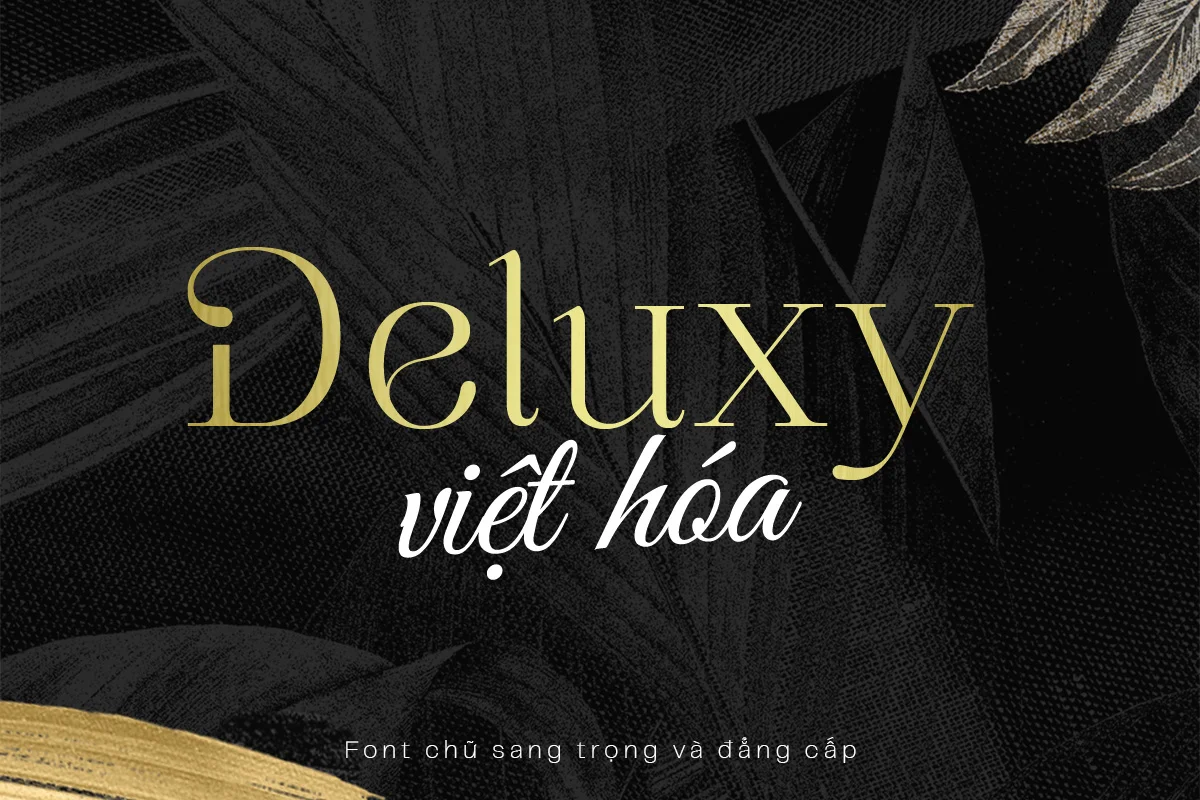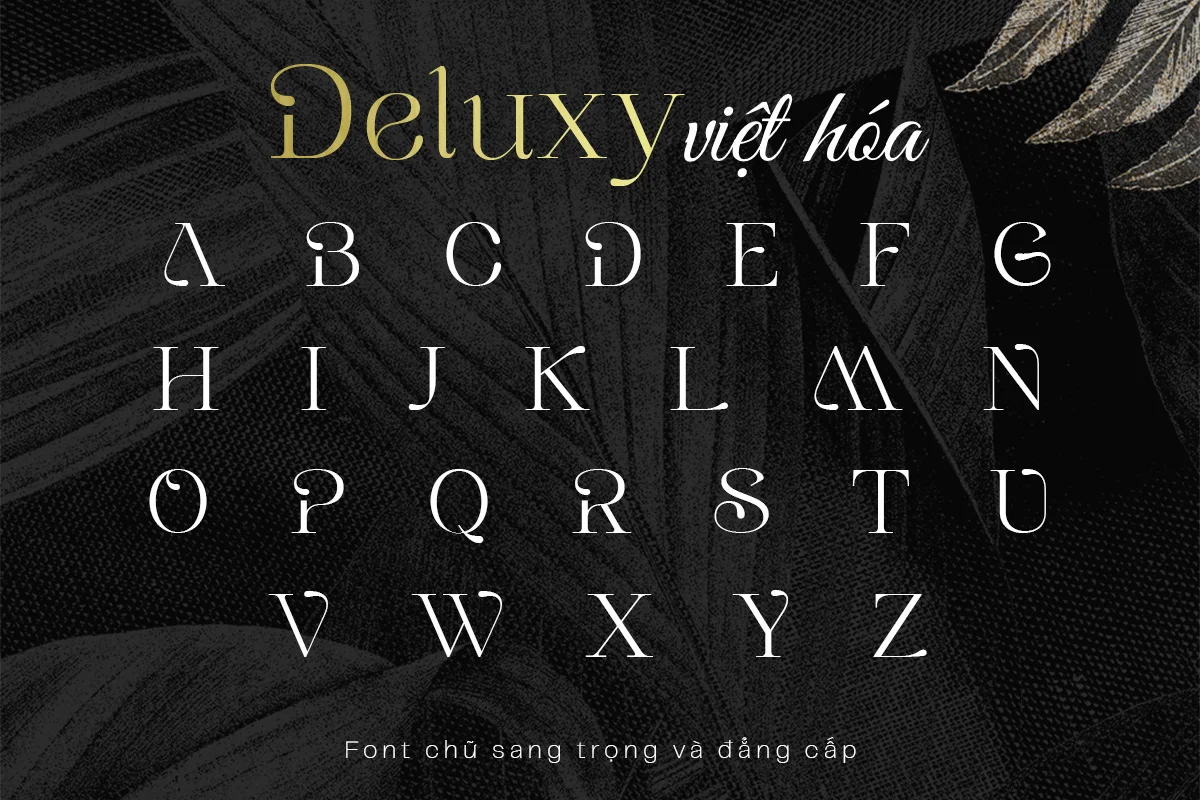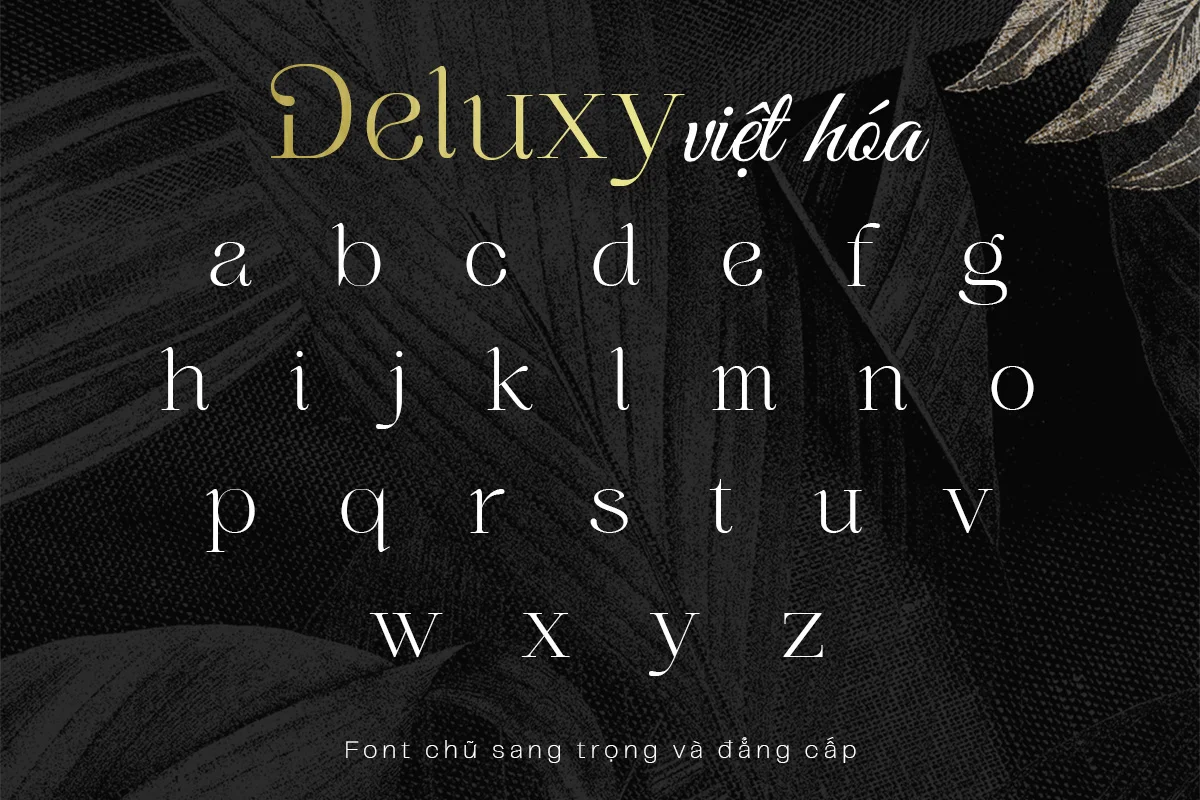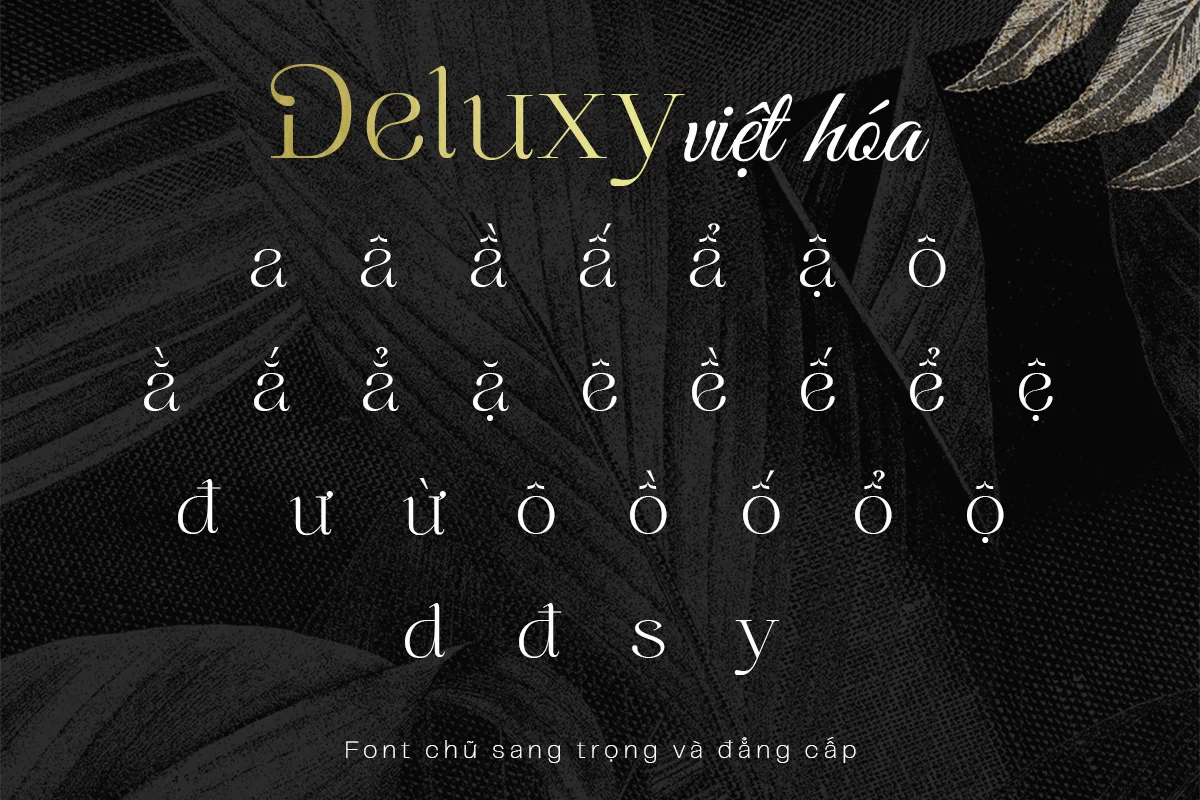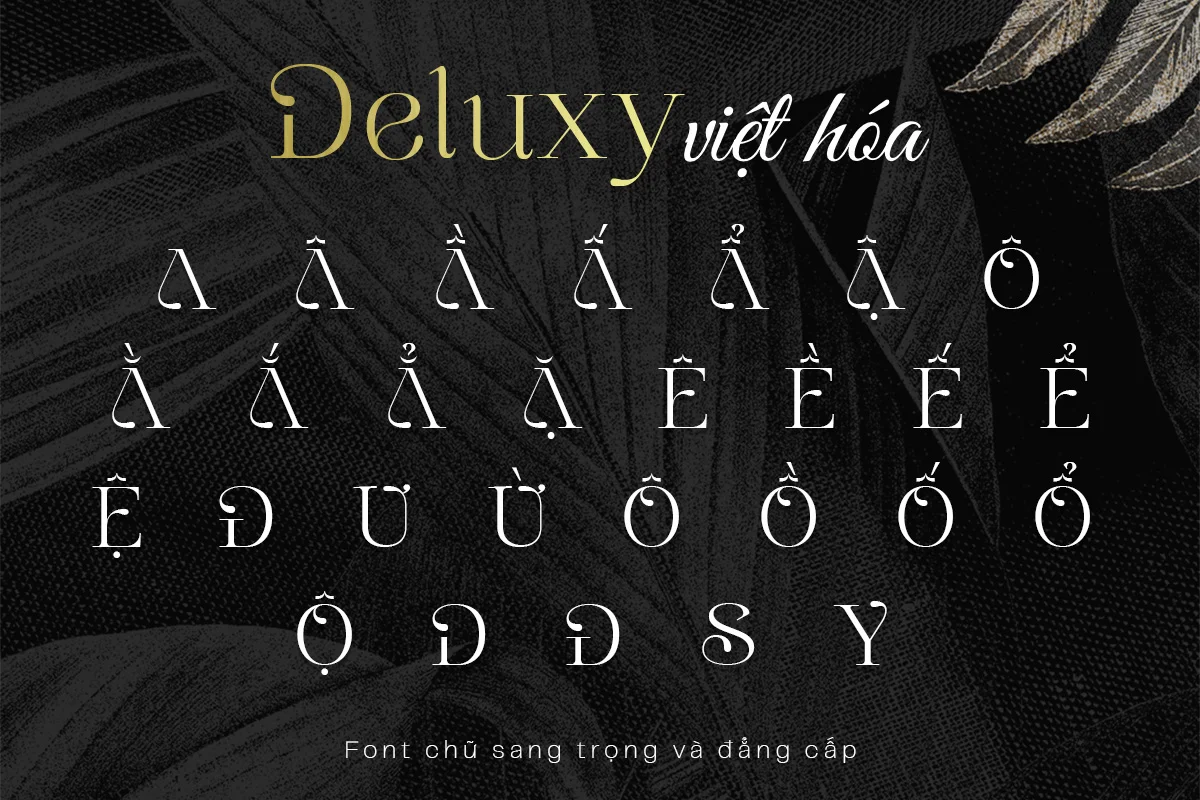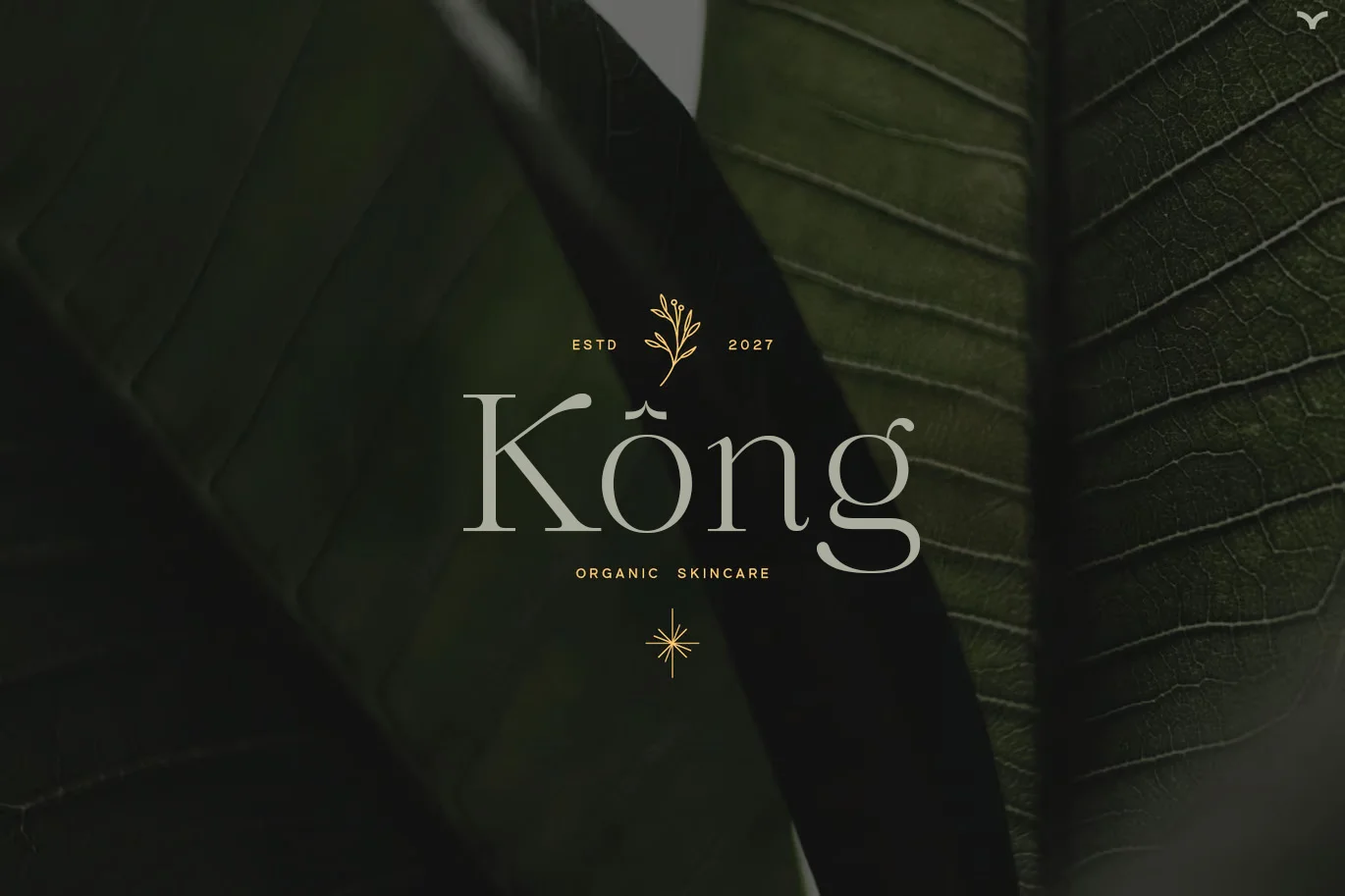
DVN Deluxy Việt Hóa là một phông chữ serif tinh tế, mang đậm phong cách sang trọng và hiện đại, lý tưởng cho các dự án thiết kế cao cấp. Với các nét chữ thanh thoát, chuyển đổi mượt mà giữa nét đậm và nét mảnh, font chữ này mang lại cảm giác quý phái, chuyên nghiệp. Được Việt hóa hoàn chỉnh, DVN Deluxy hỗ trợ đầy đủ tiếng Việt, đảm bảo hiển thị chính xác và đẹp mắt trên mọi ấn phẩm. Phông chữ này hoàn hảo cho thiết kế logo, bao bì, tiêu đề tạp chí, thiệp mời, hoặc các dự án thương hiệu cao cấp. Sự kết hợp giữa vẻ đẹp cổ điển và hơi thở đương đại khiến DVN Deluxy trở thành lựa chọn không thể bỏ qua cho các nhà thiết kế muốn nâng tầm sáng tạo. Hãy thử ngay để tạo nên những thiết kế ấn tượng!